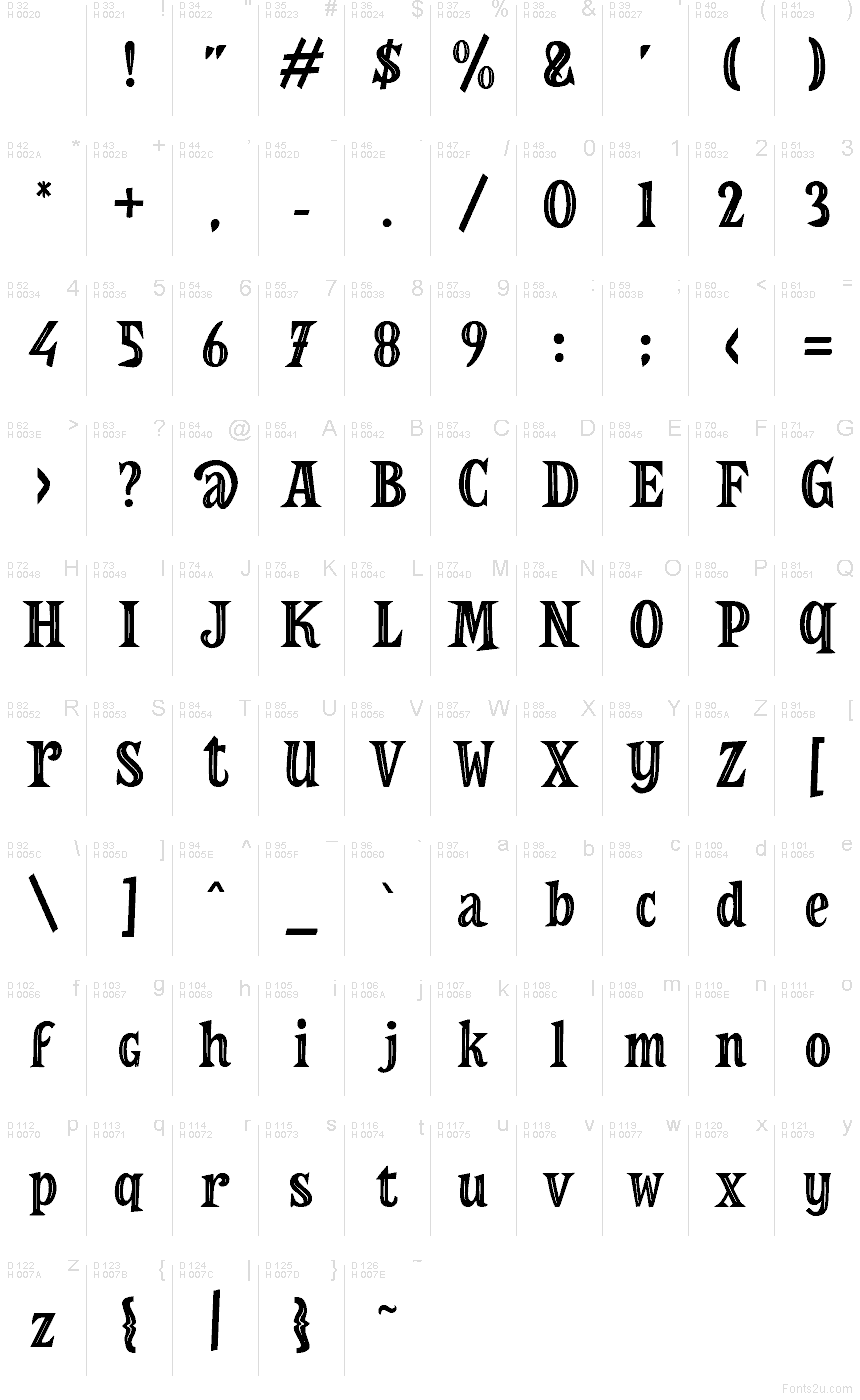
La Souris et les Corbeaux od BlackFridayFont je bezplatné písmo typu display, které vyniká vysokou, teatrální siluetou a nezaměnitelným duchem francouzských plakátů. Písmo střídá ostré, klínovité patky, výrazné křivky a úzké vnitřní linie, což celému návrhu dodává texturu připomínající řezbu či divadelní nápis spíše než pouhý dekorativní doplněk.
Tato kombinace dává dokonalý smysl na obálkách knih, butikovém balení, vinných etiketách, brandingu restaurací či plakátech na akce, kde je potřeba dramatický akcent. Zejména krátké nadpisy a názvy těží z prodloužených tvarů a vysoce kontrastních křivek, které jim dodávají formální, lehce tajemnou přítomnost, aniž by působily jako laciný efekt.